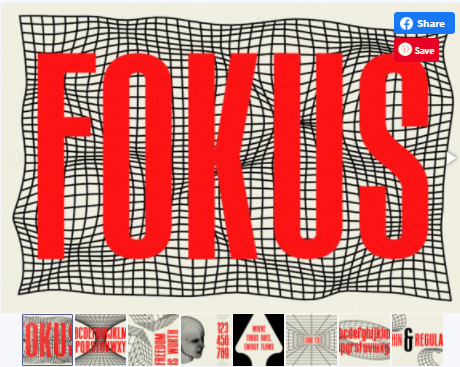
Fokus Font
Fokus - это стильный жирный шрифт с толстыми буквами. Он будет потрясающе смотреться на любом меню еды, плакате, флаере или принте.
Используйте этот шрифт для своих проектов и исследуйте его безграничные возможности.
Fokus - это стильный жирный шрифт с толстыми буквами. Он будет потрясающе смотреться на любом меню еды, плакате, флаере или принте.
Используйте этот шрифт для своих проектов и исследуйте его безграничные возможности.